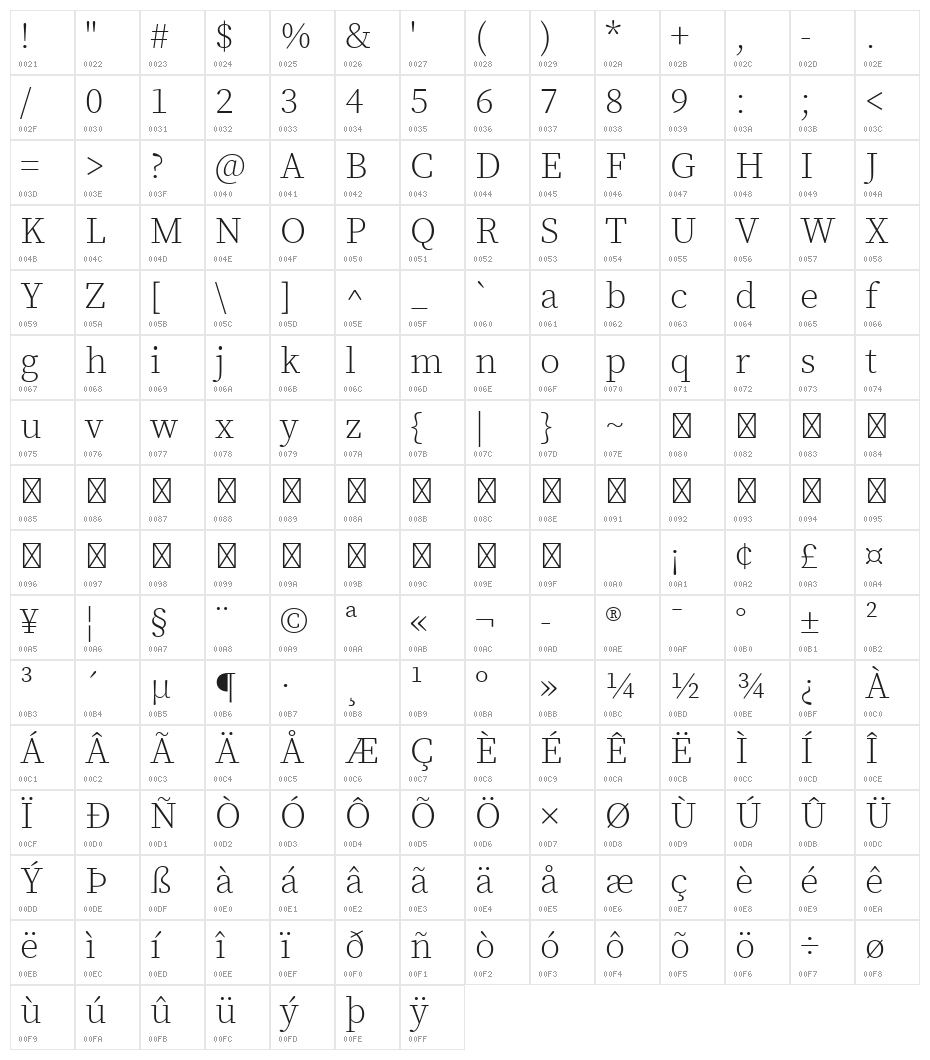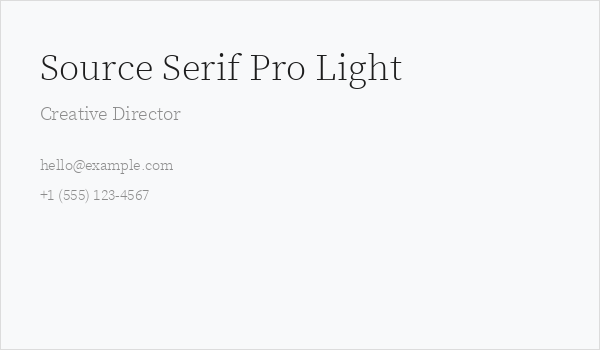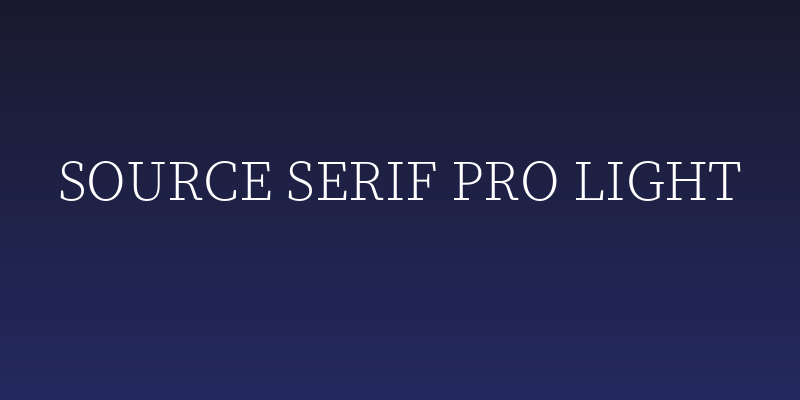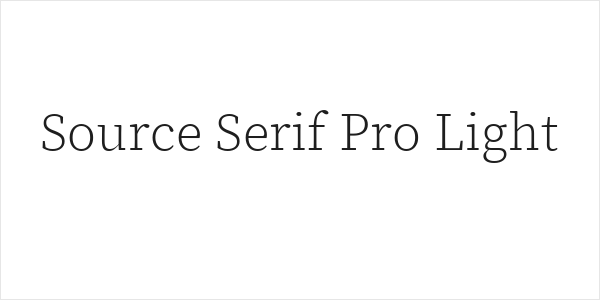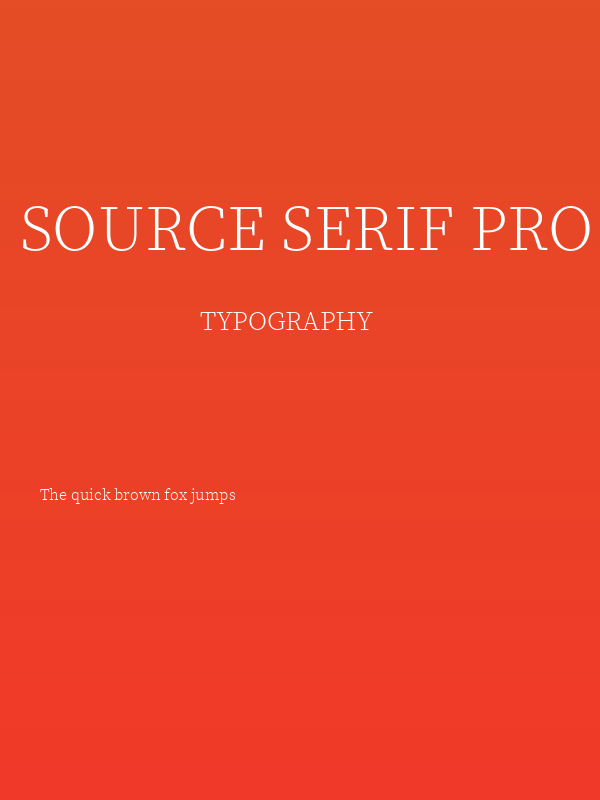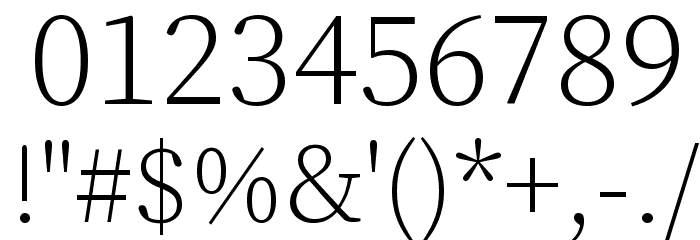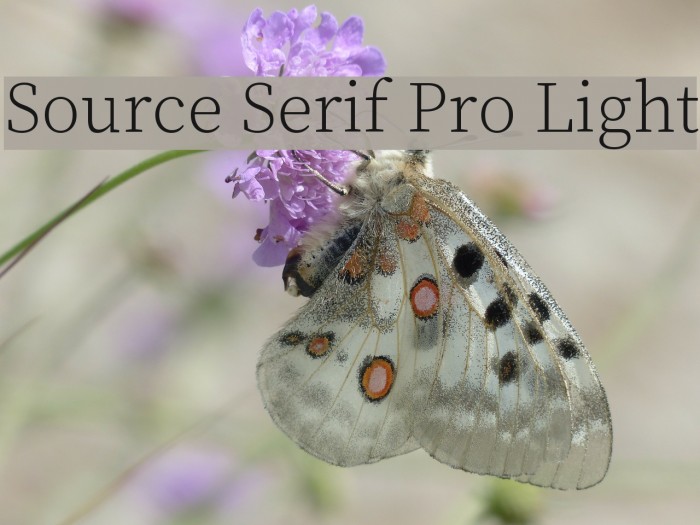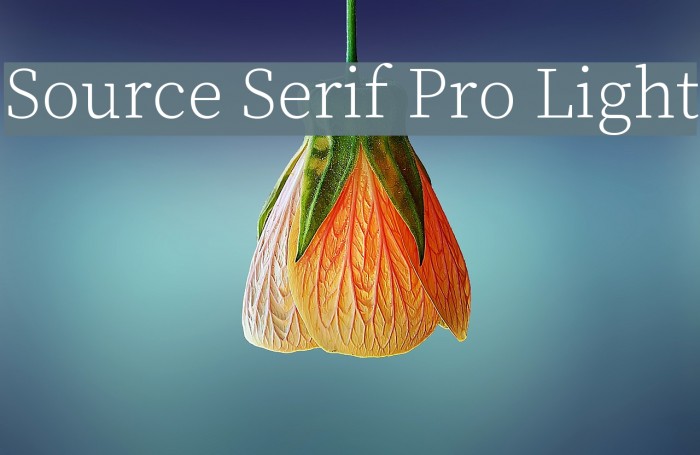
Source Serif Pro Light Font
| Caso de uso | Body text, Headlines, Editorial design |
| Projetos propostos | Ideal for editorial design, book publishing, formal invitations, and branding projects that require a touch of sophistication. |